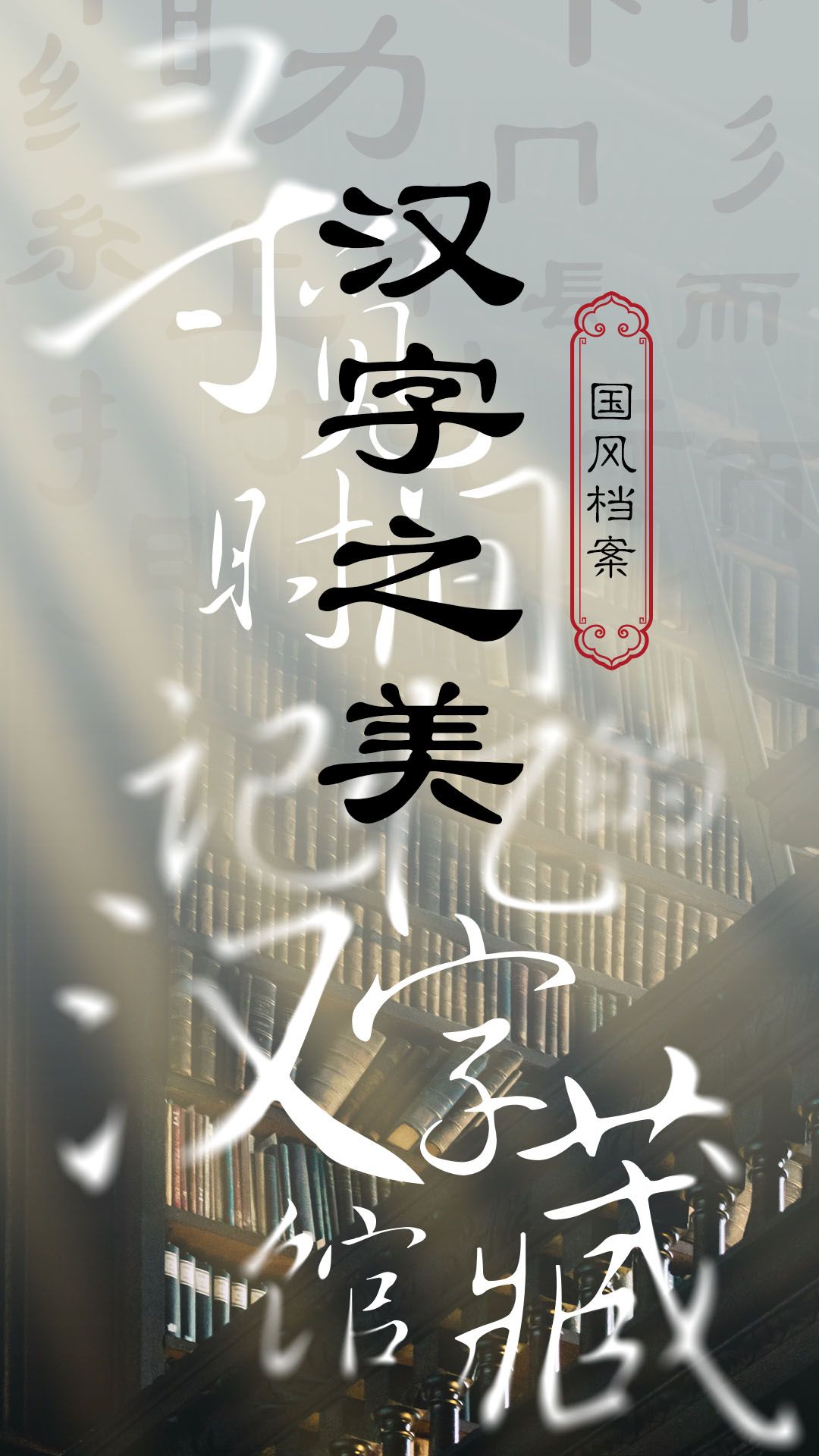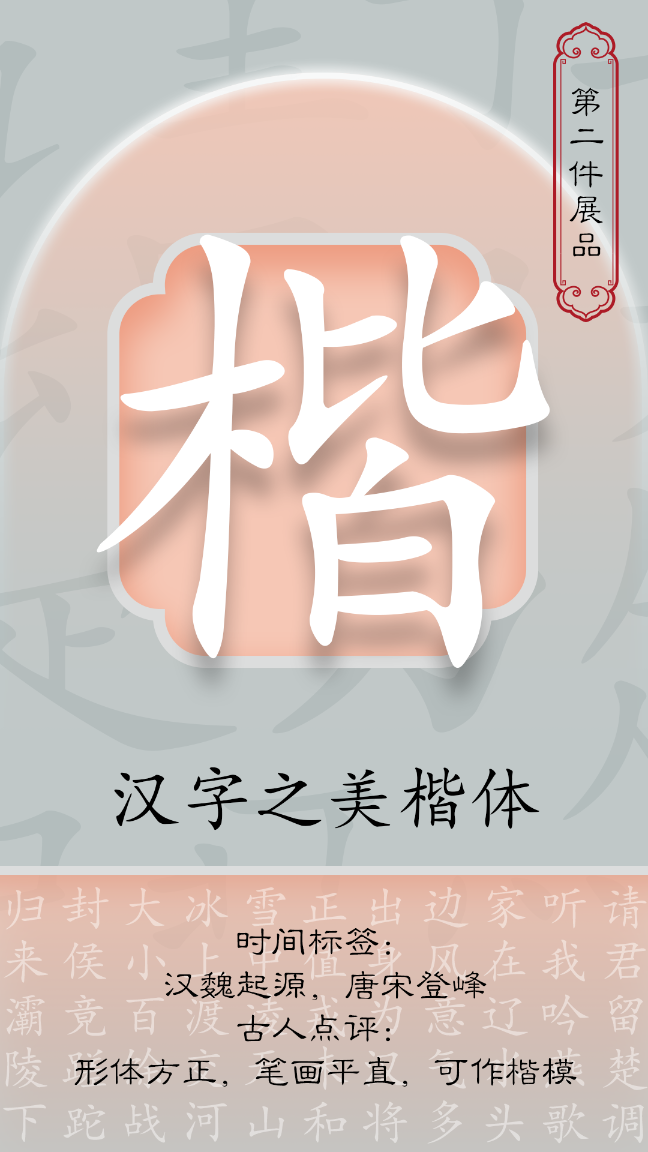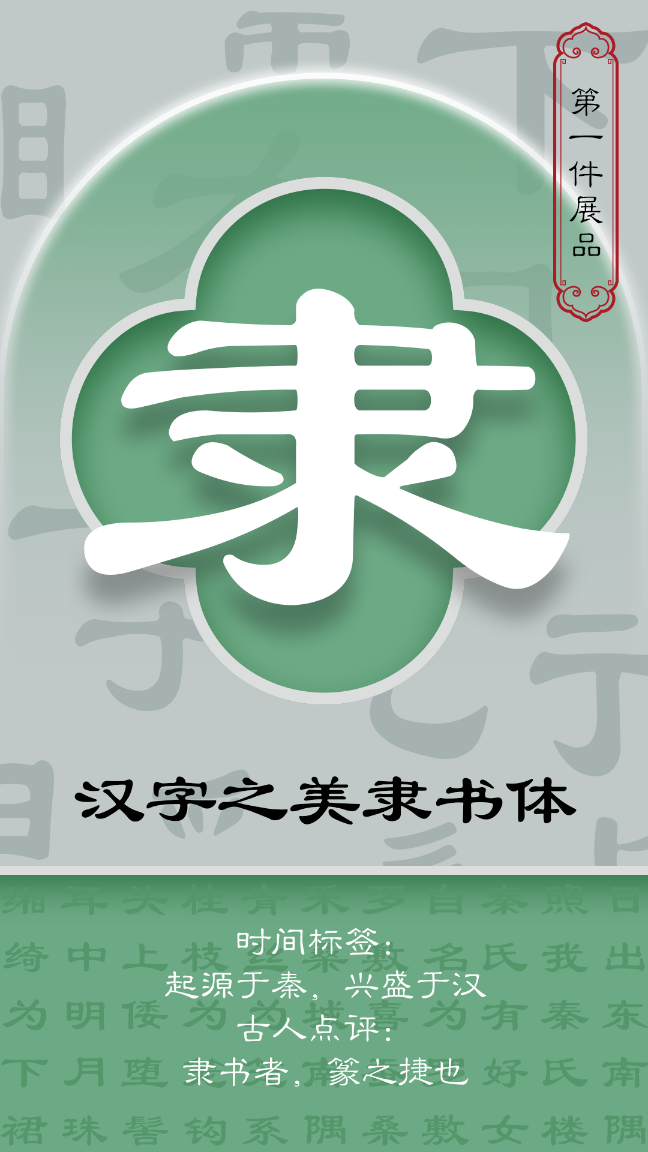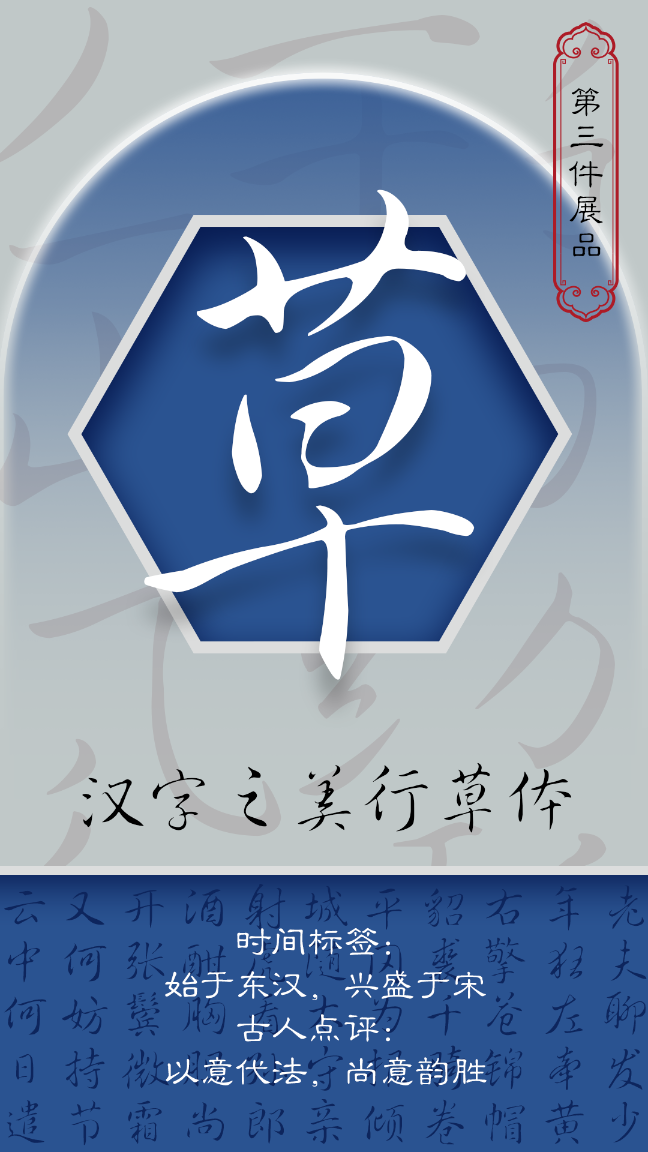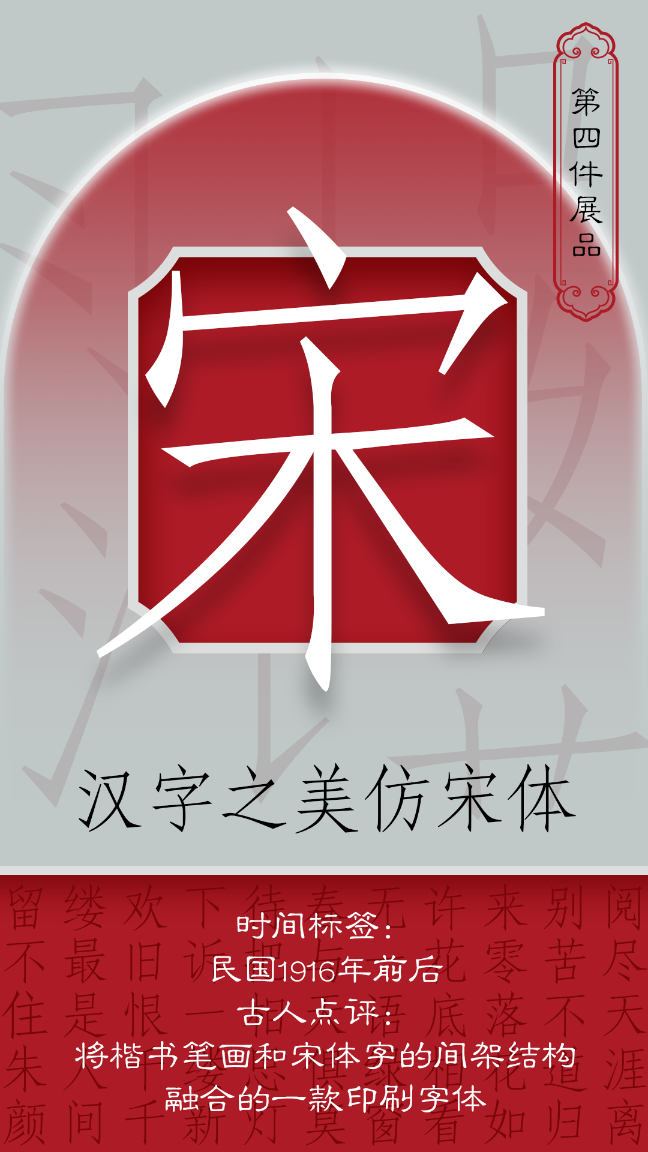
汉字之美国风档案 | 寻觅时间记忆的汉字馆藏
浩瀚的汉字宝藏,容纳了六千年间人类诗歌繁衍的文字记忆。每一款汉字不仅仅是一个文字符号,其中蕴含的时代记忆、人类智慧才是其中最生动的部分。
跟随字神国风字库一起阅览汉字藏馆,探寻汉字背后的时代记忆。
展品一
展品名称:汉字之美隶书体
时间标签:起源于秦,兴盛于汉
古人点评:隶书者,篆之捷也。
展品介绍:隶书是颇具古韵的一款字体,碑刻之风盛行的时代,赋予隶书更多的时代烙印。
展品二
展品名称:汉字之美楷体
时间标签:汉魏起源,唐宋登峰
古人点评:形体方正,笔画平直,可作楷模
展品介绍:楷书开辟了以法为标准的审美空间,创造了中国书法辉煌灿烂的楷书之法度。
展品三
展品名称:汉字之美行草体
时间标签:始于东汉,兴盛于宋
古人点评:以意代法,尚意韵胜
展品介绍:宋代璀璨斑斓的文化风貌,给了书法多元的演变方向,行书尚韵,君子和而不同,美美与共。
展品四
展品名称:汉字之美仿宋体
时间标签:民国1916年前后
古人点评:将楷书笔画和宋体字的间架结构融合的一款印刷字体
展品介绍:兼具古典文化与现代审美的仿宋体,仿佛是一张穿梭于旧时光的门票,置身于油墨飘香的民国,又徜徉在物质丰盛的现代。